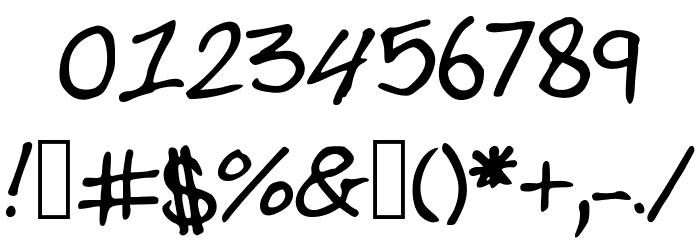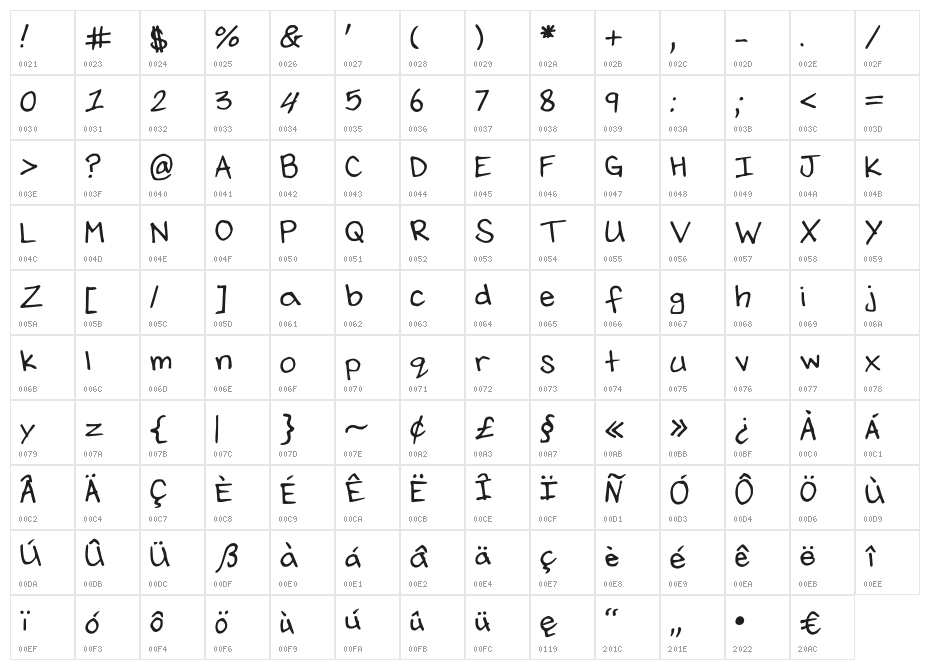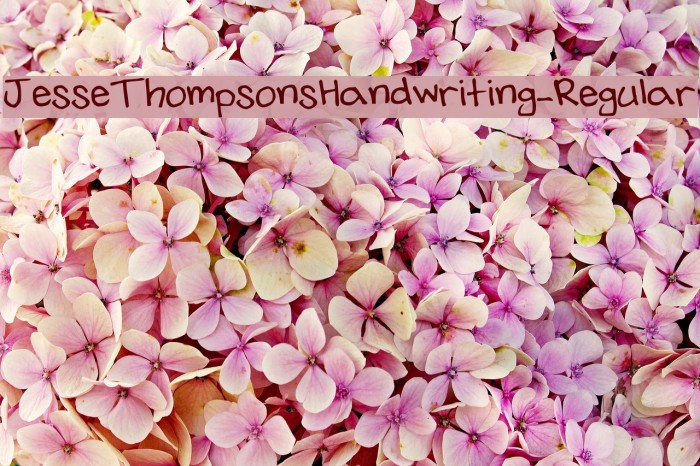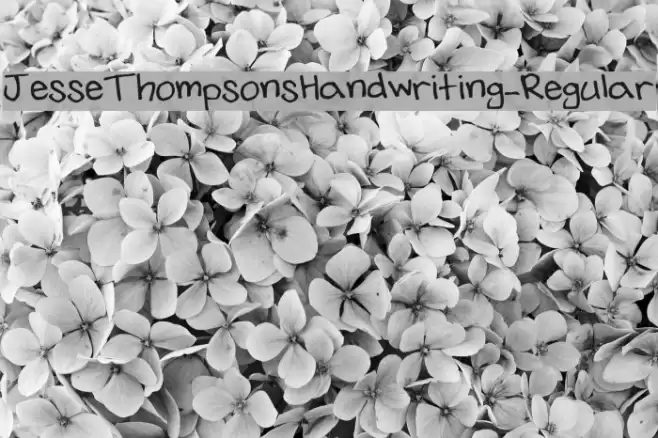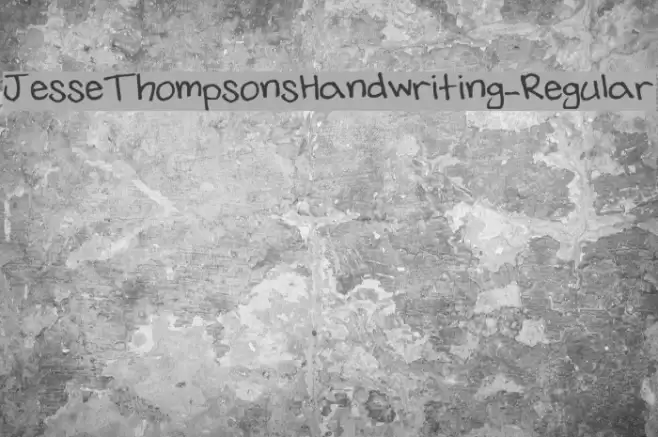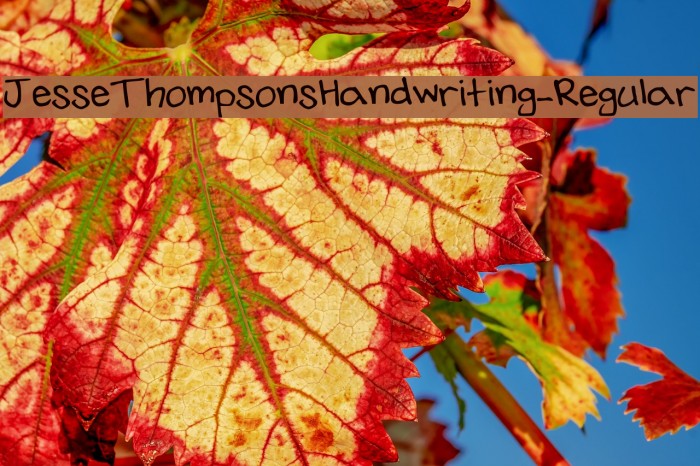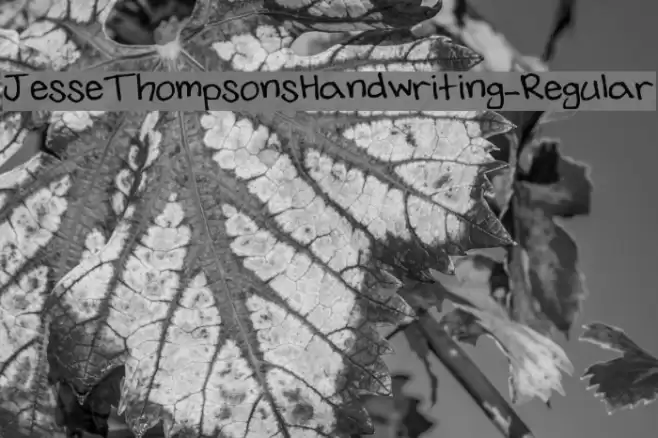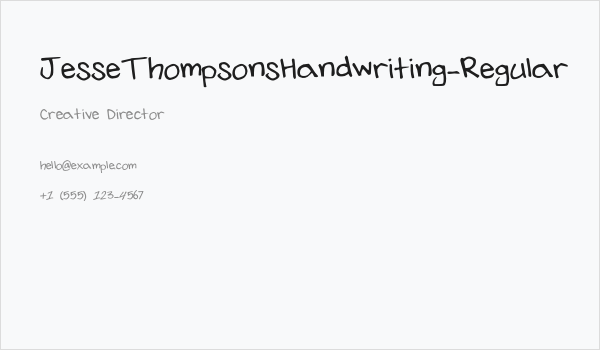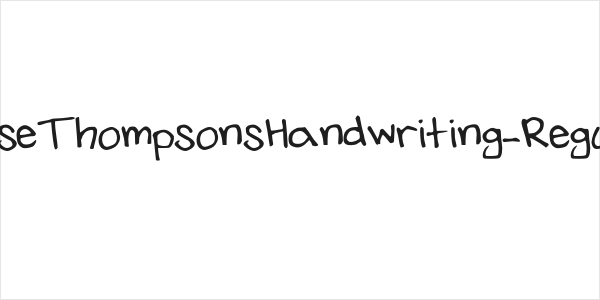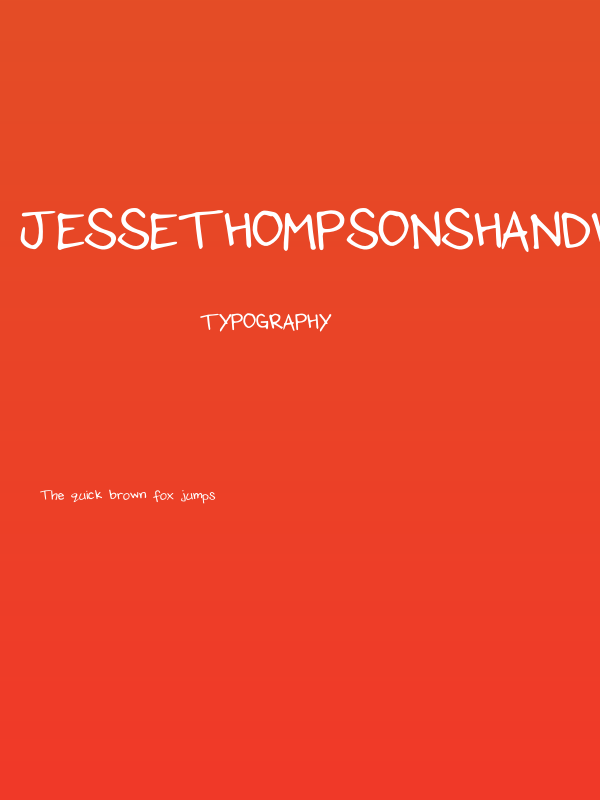
JesseThompsonsHandwriting-Regular Font
✎ Handwritten
| समग्र शैली | Casual, Playful |
| उपयोग का मामला | Headlines, Informal text, Creative projects |
| सुझाए गए प्रोजेक्ट | Ideal for greeting cards, personal notes, children's books, and creative projects that require a friendly and informal tone. |